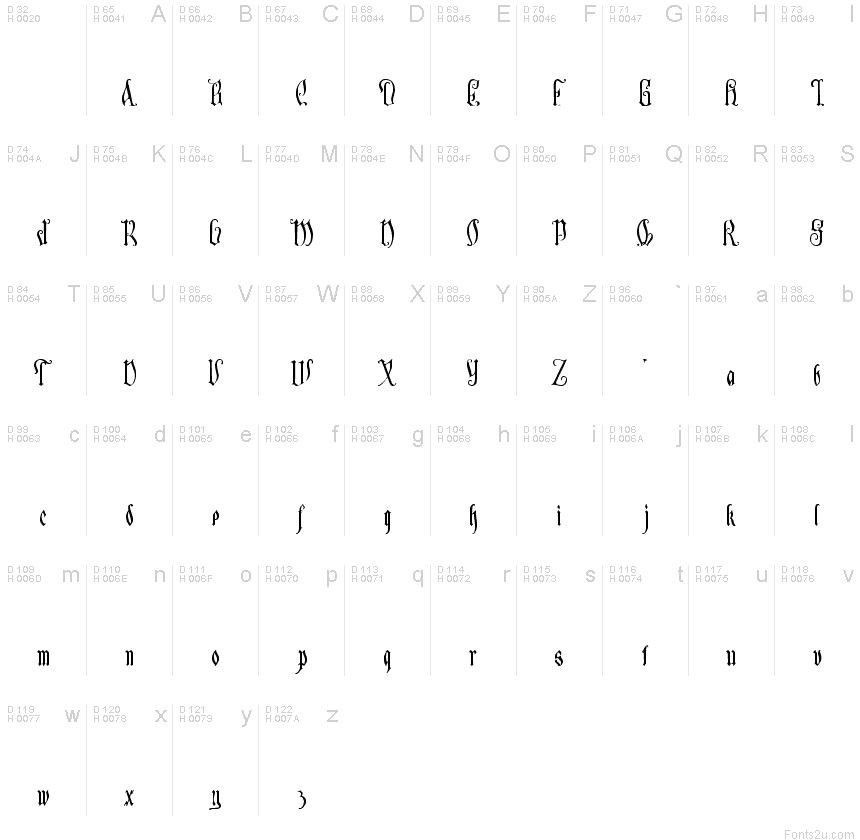
Manticore autorstwa Davida F. Nalle to darmowy, średniowieczny krój gotycki. Wyróżniają go wysokie pociągnięcia w stylu blackletter, ostre, diamentowe cięcia i haczykowate wygięcia, które nadają literom napięty, pionowy rytm. Tekstura pozostaje mroczna i ceremonialna, ale dzięki częstym zwężeniom i ostrym krawędziom krój nie sprawia wrażenia topornego ani ciężkiego.
To sprawia, że Manticore jest naturalnym wyborem na okładki książek fantasy, plakaty z jarmarków renesansowych, tytuły gier, szyldy pubów i otwarcia rozdziałów, które wymagają historycznego sznytu, a nie generycznej gotyckiej stylistyki. Krój najlepiej sprawdza się w krótkich nagłówkach i logotypach, ponieważ wąski pionowy układ i ostre detale tworzą formalny klimat, przywodzący na myśl dawne rękopisy.